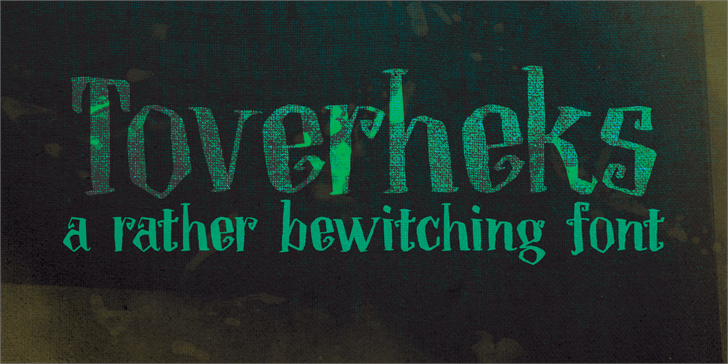
DK Toverheks Font
A fonte DK Toverheks é uma serif sem-serif que oferece um equilíbrio atraente entre elegância tipográfica e funcionalidade pronta para uso. Seu designer, Hamilton, criou essa fonte como uma versão básica do famoso tipo “Toverheks”, disponível gratuitamente apenas para uso pessoal. Os usuários podem experimentar o estilo sóbrio dessa fonte em criações digitais de textos e gráficos que não requerem permissões comerciais. Para usá-la comercialmente, é necessário adquirir a versão completa, que oferece recursos adicionais como alinhamento de espaçamento (kerning), direitos de embedder, todos os caracteres incluídos em seu conjunto (incluindo o número 4) e extras disponíveis exclusivamente no site do designer: hanodedfonts.com. A fonte DK Toverheks é adequada para diversos usos gráficos, mas infelizmente não pode ser utilizada em jogos, aplicações ou software de código aberto. Para obter uma licença comercial, consulte o site oficial do designer: www.hanodedfonts.com. Além disso, você encontrará informações adicionais e respostas a perguntas frequentes (FAQ) no arquivo zip inclusivo dessa fonte, permitindo que você utilize essa font de maneira responsável e legalmente.